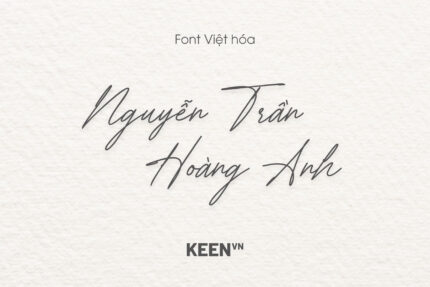
Font Việt hóa Oai Pork Belly
- Hỗ trợ đầy đủ dấu tiếng Việt
Mô tả
Font Việt hóa OAI Pork Belly mang phong cách chữ ký tự nhiên với các nét viết liền mạch, tạo cảm giác như được viết nhanh bằng bút mực trên giấy. Đặc trưng dễ nhận thấy của kiểu chữ này nằm ở những đường nét mảnh, hơi nghiêng và có độ biến thiên nhẹ về lực nét, giúp tổng thể chữ trông mềm mại và giàu tính cá nhân. Các ký tự được thiết kế với độ nối hợp lý giữa các chữ cái, khiến dòng chữ trở nên trôi chảy và mang cảm giác phóng khoáng, gần với chữ ký tay của một người thật. Khi được Việt hóa, hệ dấu tiếng Việt được đặt gọn gàng theo trục nghiêng của chữ, giữ được sự tự nhiên mà không làm phá vỡ nhịp điệu viết tay đặc trưng.
Với tinh thần thân thiện và mang dấu ấn cá nhân rõ rệt, OAI Pork Belly phù hợp cho các thiết kế chữ ký thương hiệu, watermark cá nhân, thiệp chúc mừng, quote nghệ thuật, bao bì thủ công hoặc các ấn phẩm sáng tạo cần cảm giác gần gũi và tinh tế.